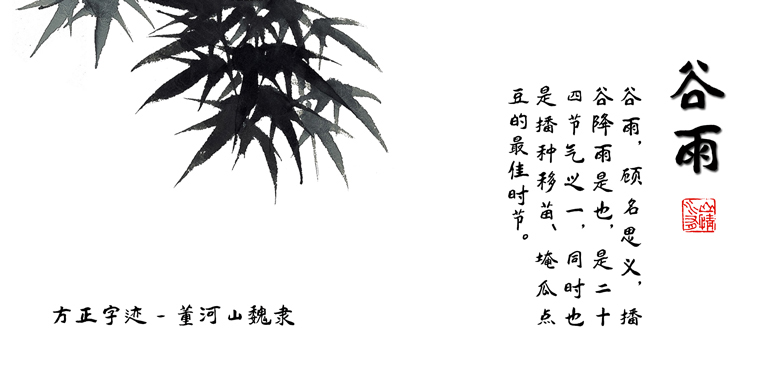
品牌:方正字迹设计师:董河山发行时间:2018字库编码:简繁扩展(GBK)、大陆简体(GB2312-80)分类:常规书写·毛笔
方正字迹-董河山魏隶是方正字库2018年出品的一款非常漂亮的艺术字体,字体风格介于魏碑与汉隶的交界体,字形基本上承袭汉隶,但在结构上有一定变化,其特点是较汉隶方严规整其字体结构优美,风格独特,艺术个性鲜明,雅俗共赏,并有非常高的使用价值。
方正字迹-董河山魏隶 ,广泛用于各种书刊、画册的设计印刷中,字体具有强烈的视觉冲击力,是报纸和杂志和书籍中常用字体, 应用于海报、个性促进品牌标志设计、字体设计等领域。